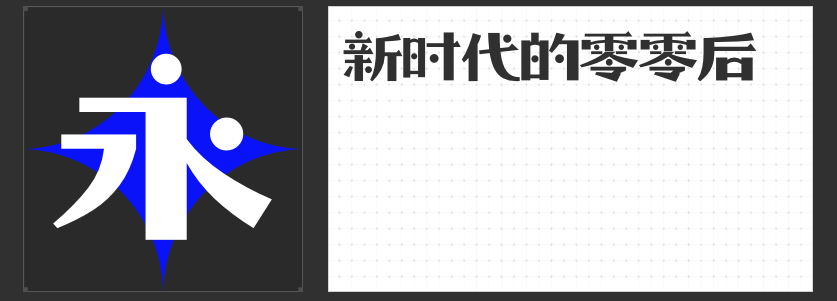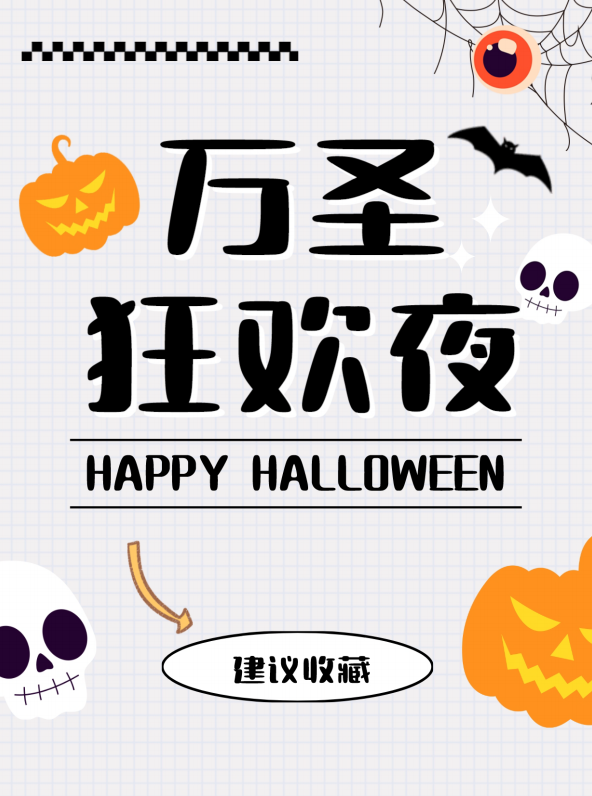
游戏世界里的字体艺术:四款游戏字体强烈推荐
在游戏的世界里,字体不仅仅是文字的载体,更是营造氛围、引导玩家情绪的关键元素。今天,就让我们一起走进四款充满创意与个性的游戏字体,感受它们在游戏中的独特魅力。
第一款推荐的是“励字暴风简 超级黑”。这款现代创意型黑体,以其厚重的字型与开放性的设计,打破了传统黑体的沉闷。笔画粗细不均,横竖笔画梯形分布,撇、捺、点中融入梯形元素,整体风格硬朗而富有现代文艺气息。在游戏中,它能为场景增添一份独特的视觉冲击力。
接下来是“高手庆科巧克力 大圆”。这款宽扁的圆体字,圆润可爱,整体平衡和谐。笔画设计简洁无过多装饰,横细竖粗,笔形圆润饱满。无论是中文还是西文符号,都保持了高度的统一性和协调性。在游戏中,它能为玩家带来温馨、舒适的视觉体验。
第三款是趣味性十足的“高手庆科数码体 大黑”。这款像素字体,用错位像素代替部分笔画,设计巧妙且富有现代感。笔画拼合与缺失的像素点相结合,既保证了字体的识别性,又增添了装饰性。无论是中文还是西文,都能在游戏中展现出独特的数码风格。
最后推荐的是“字恋狂零零后简繁”。这款字体中融入了圆形小球元素,无规则地散落在每个字中,显得调皮可爱。部分笔画设计成拱形的弧线,曲直结合,相映成趣。在游戏中,它能为玩家带来一份轻松愉快的氛围。
四款字体各具特色,无论是硬朗的“励字暴风简 超级黑”,还是圆润的“高手庆科巧克力 大圆”,或是趣味十足的“高手庆科数码体 大黑”,以及可爱的“字恋狂零零后简繁”,都能在游戏中为玩家带来不一样的视觉享受。快来挑选一款你喜欢的字体,为你的游戏世界增添一份独特的魅力吧!